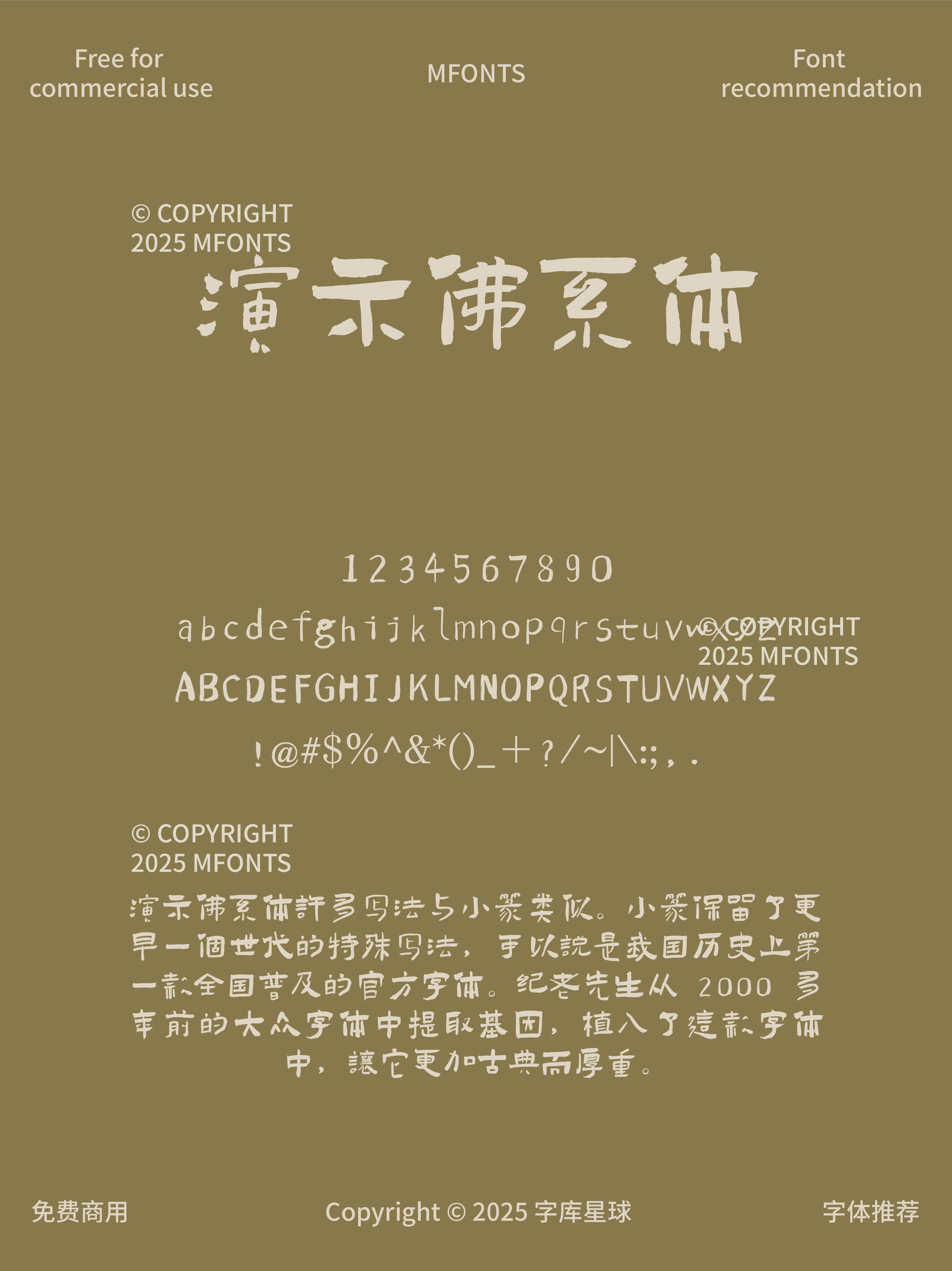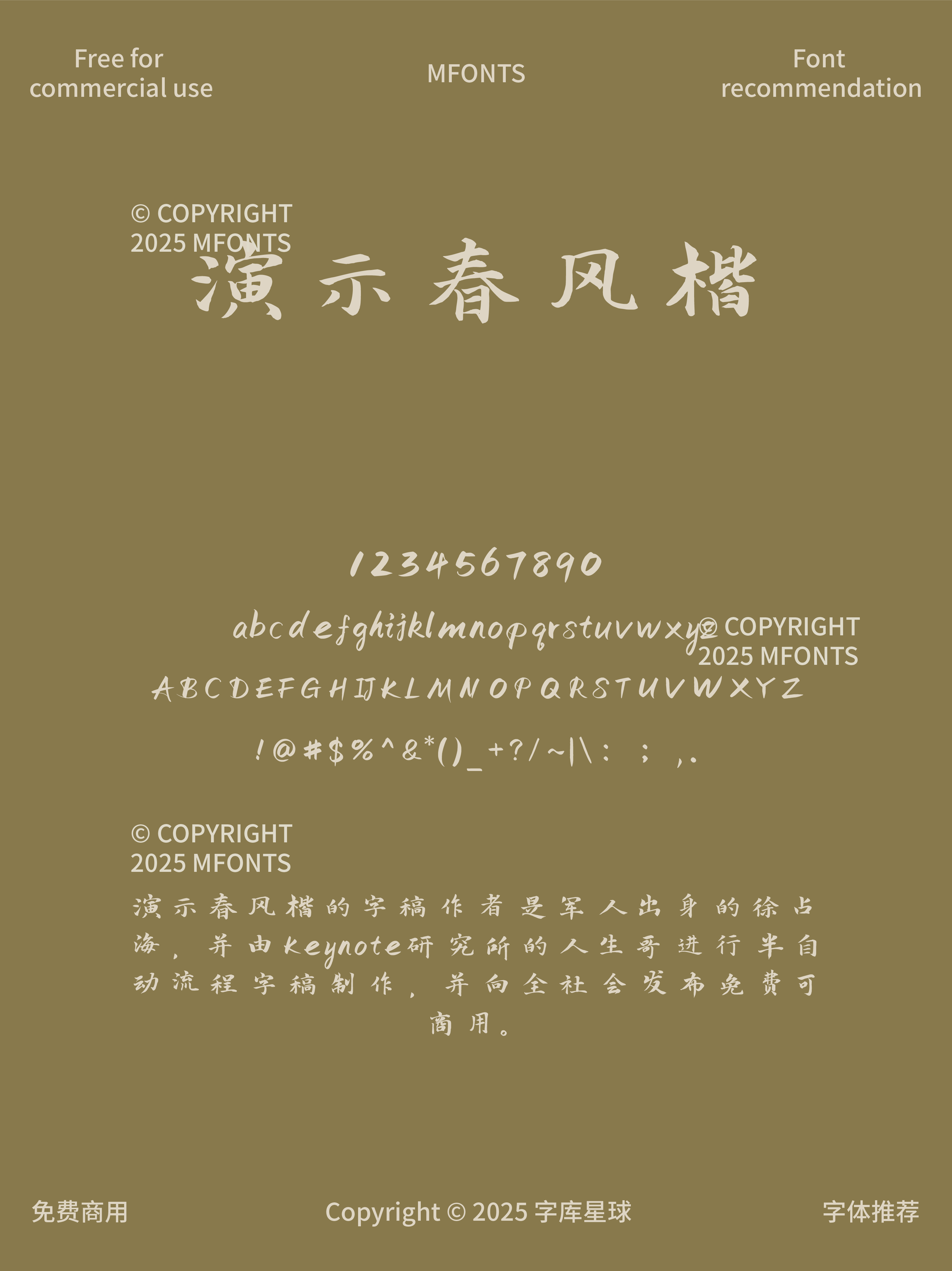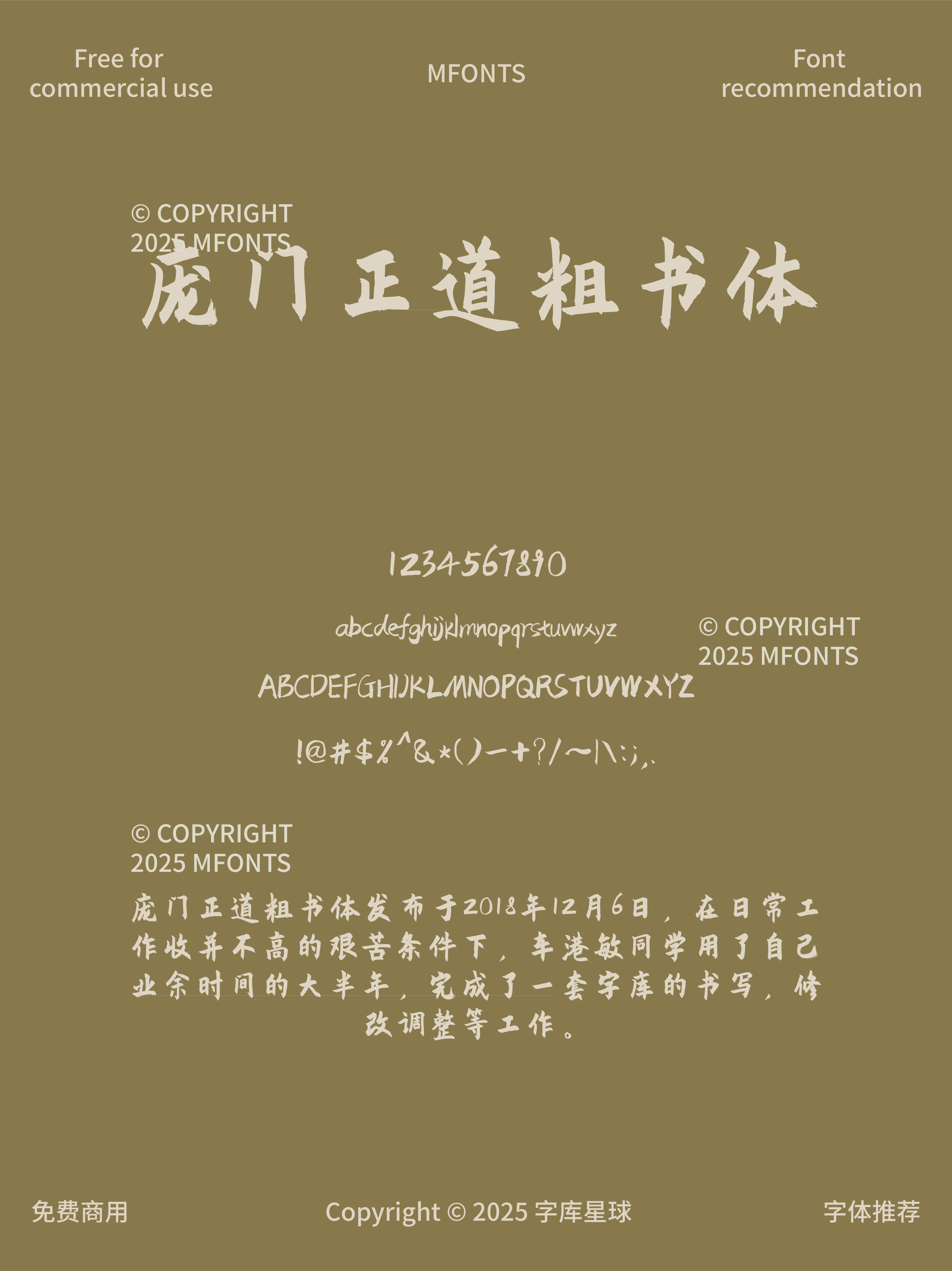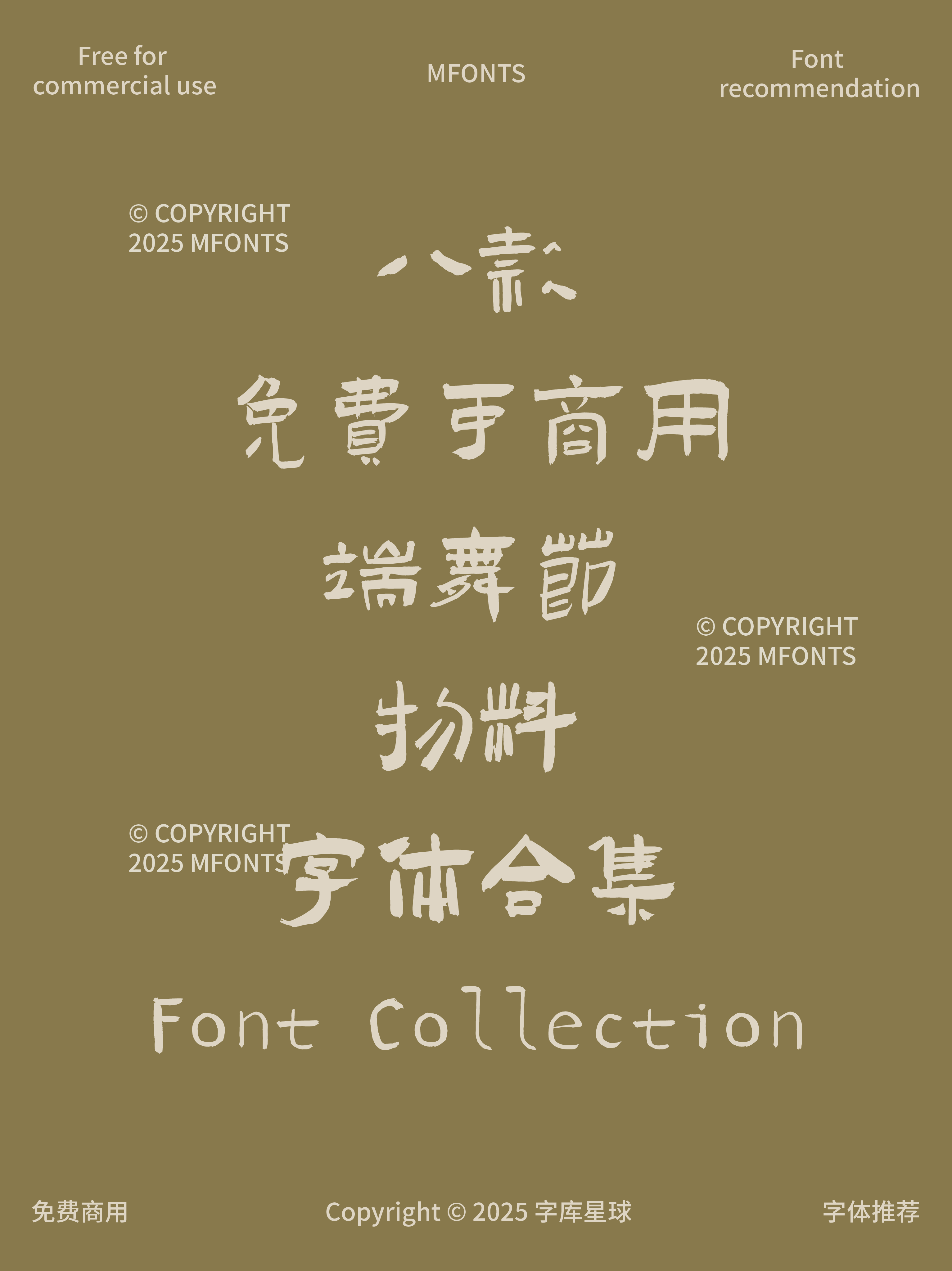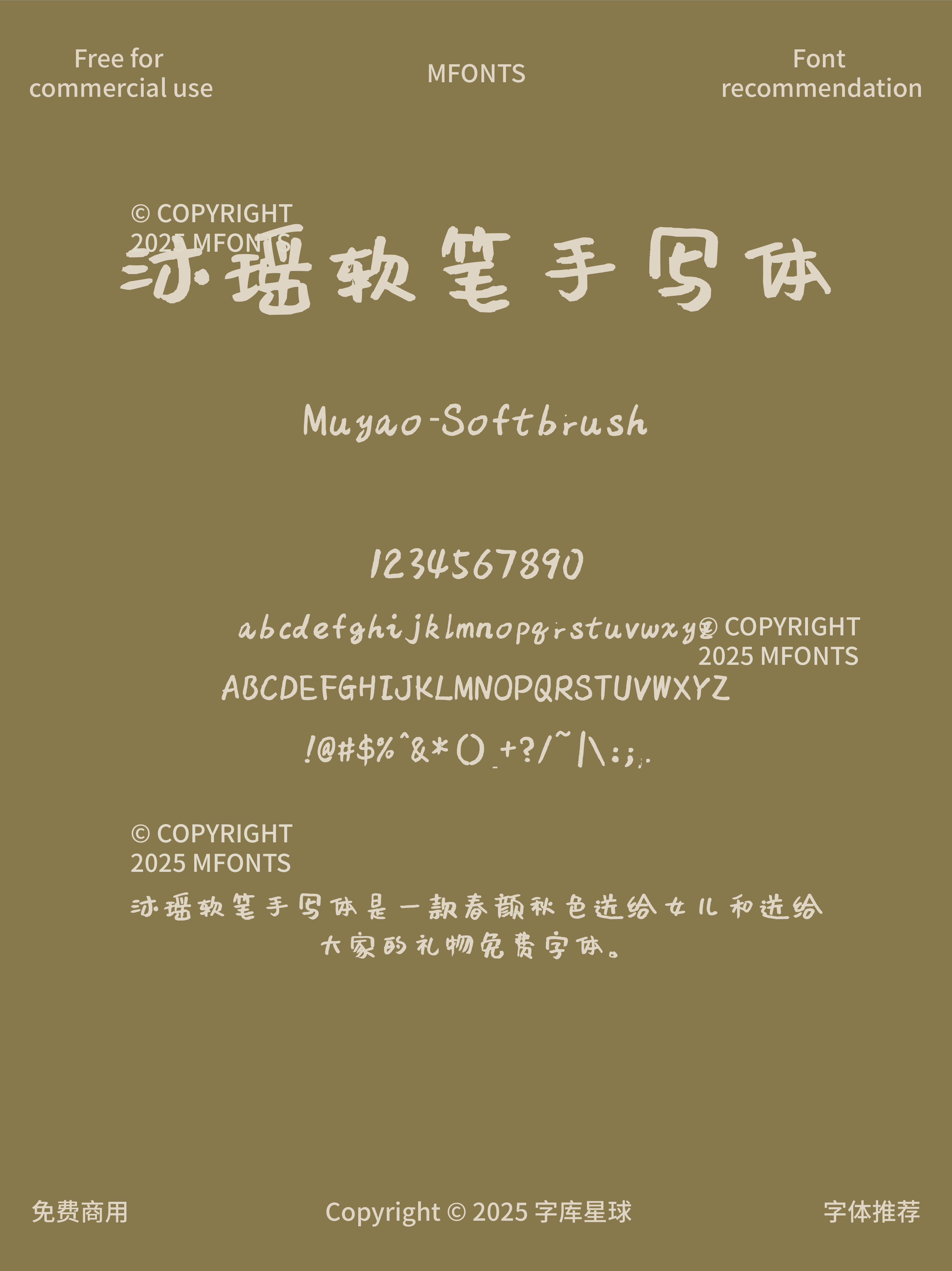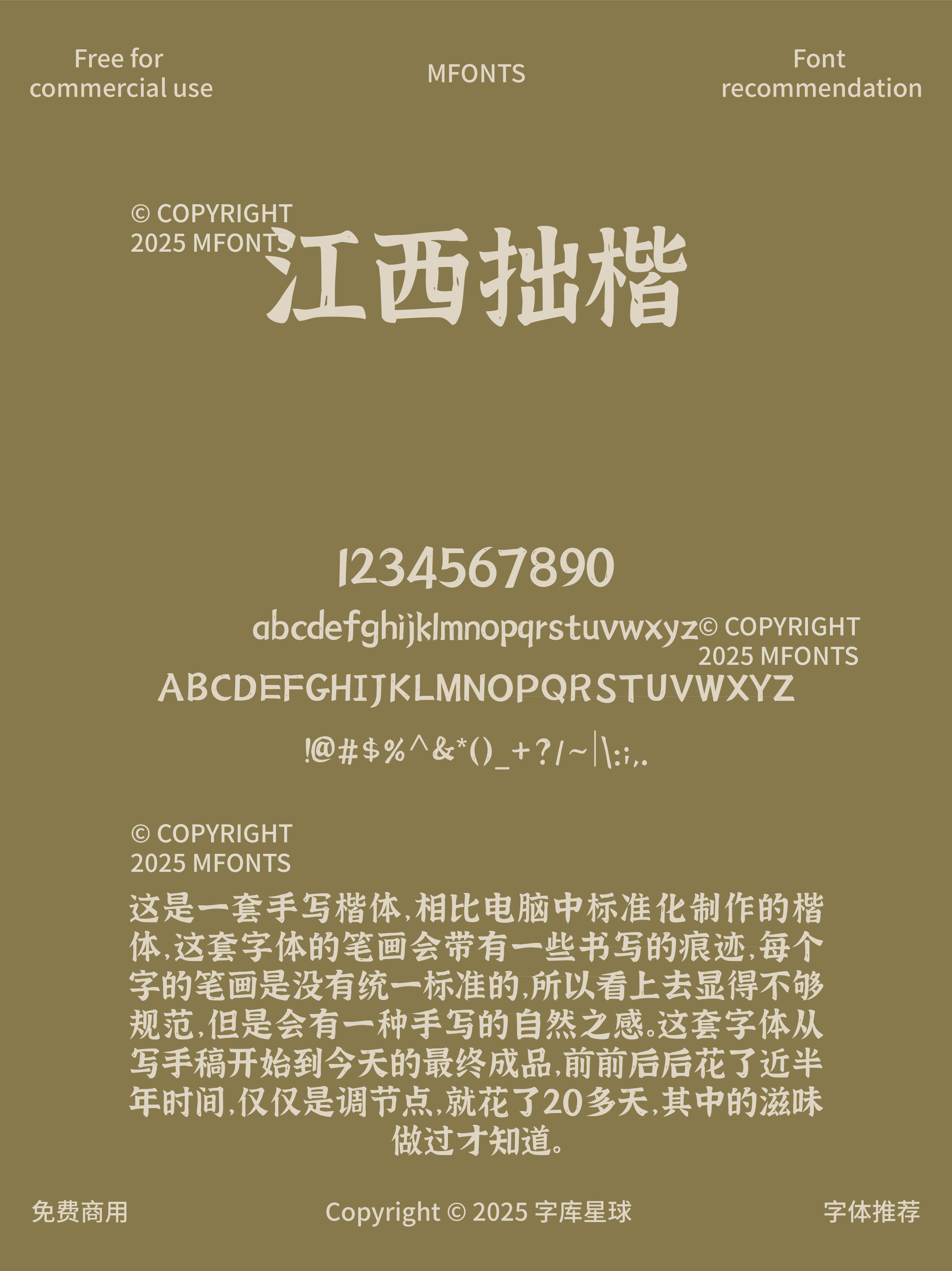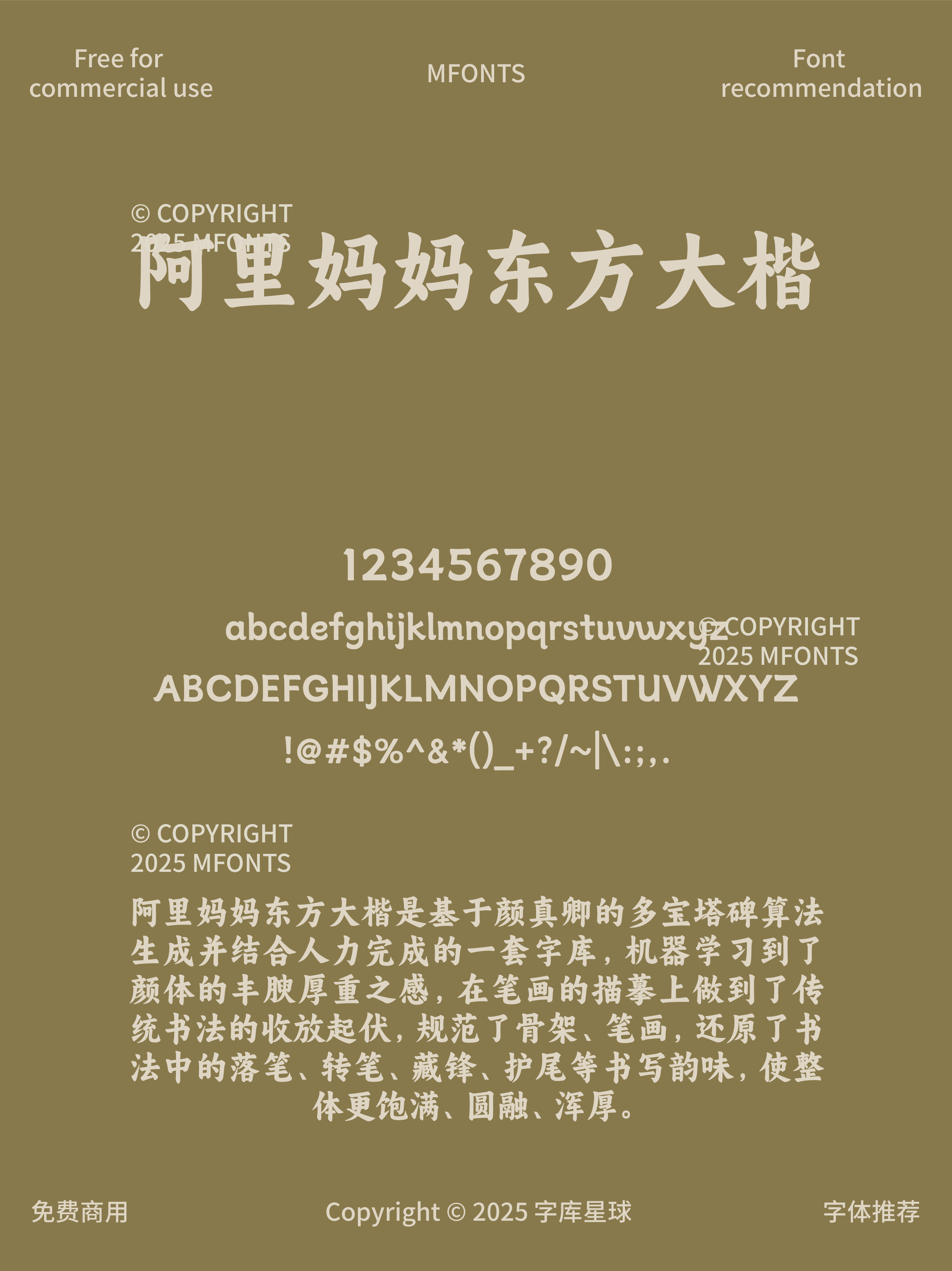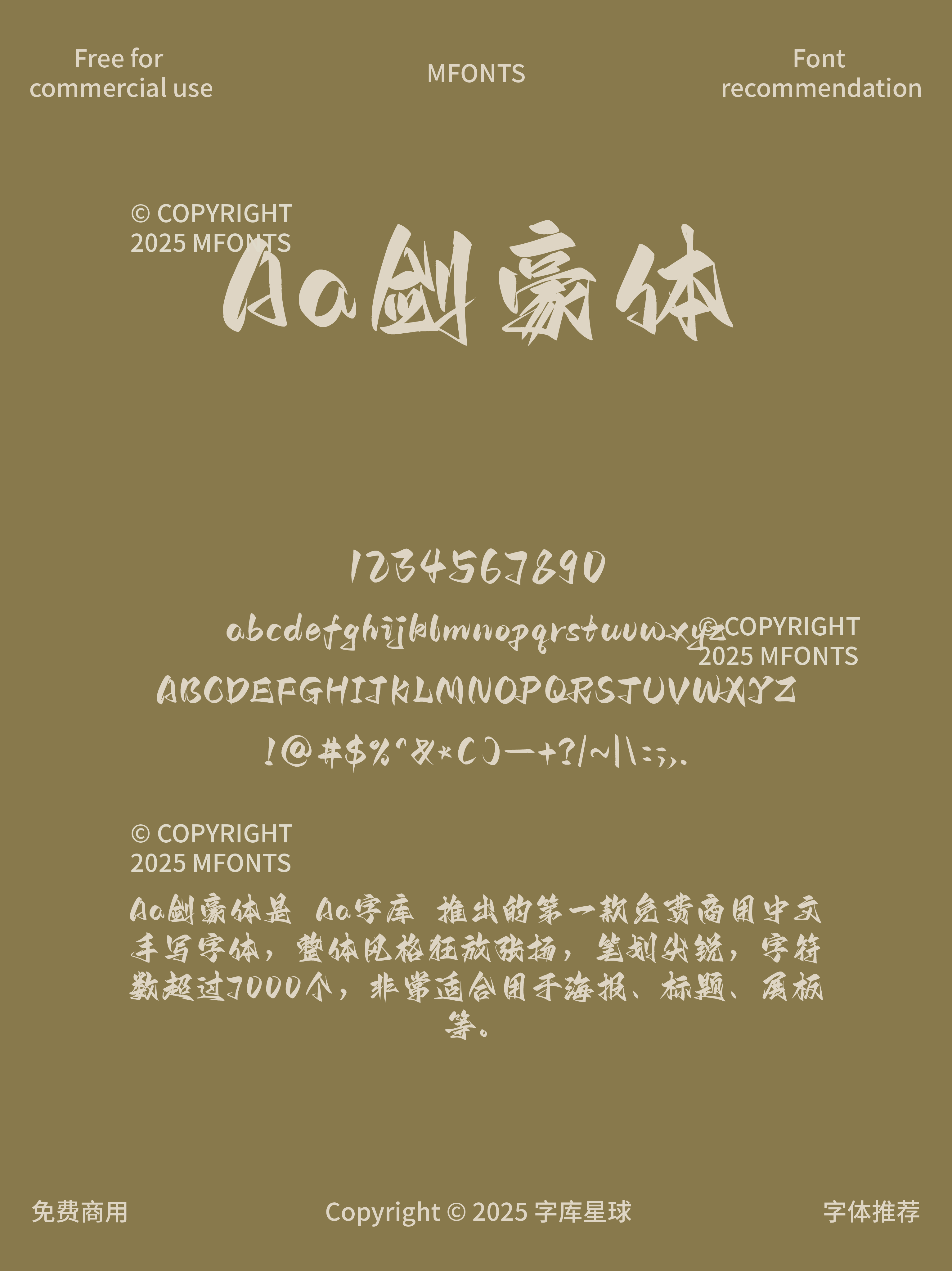
八款免费可商用端午节物料字体
宝子们,端午将至,是不是在为找合适的字体而发愁?别担心,今天给大家分享 8 款免费可商用的端午节物料字体,让你的设计轻松出彩~
笔意如烟云般缥缈,充满文雅气质,书香气十足。用在端午诗词展示、文化宣传海报上,瞬间营造出诗意端午氛围,仿佛将人拉回那个充满古韵的时代。
古典与现代感完美融合,恰似龙舞端午时的磅礴气势。用于端午民俗活动宣传、龙舟赛事海报,能生动展现端午的热闹与激情,让画面活起来。
笔画圆润,柔中带刚,看似厚重却粗中有细,字形结构自由又不失规整严谨。整体如同润玉般光滑细腻且硬朗贵重,用在高端端午礼盒包装、品牌宣传物料上,尽显高级感。